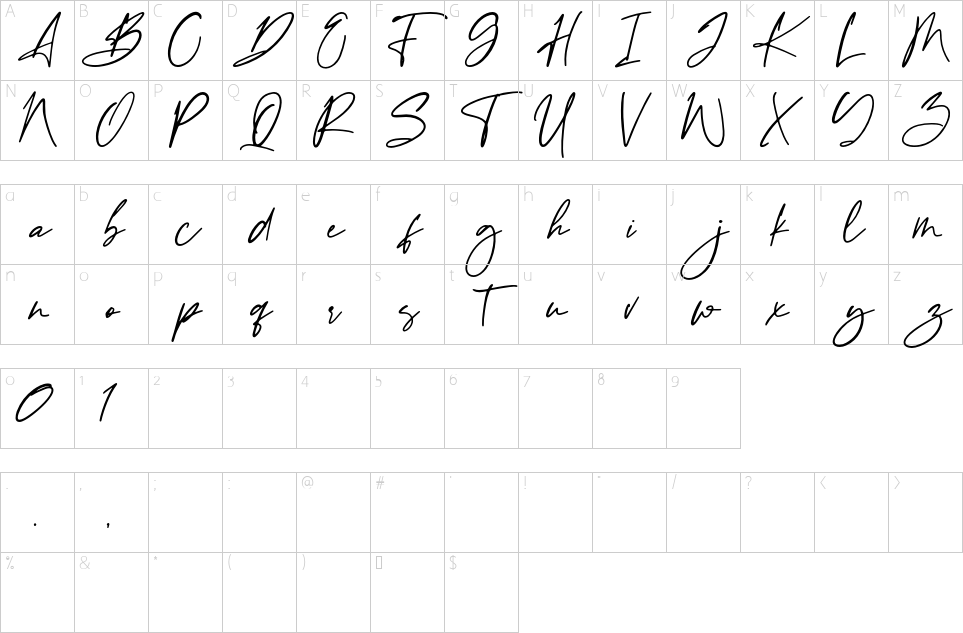
Baekrajan é uma fonte moderna e elegante que oferece um equilíbrio perfeito entre simplicidade e profissionalismo. Desenvolvida pelo designer não informado, a Baekrajan está disponível para download tanto em versão Windows quanto Mac. Com seus traços finos e formas levemente curvilíneas, esta fonte adquire um toque sofisticado às suas criações digitais. É ideal para aplicativos de design gráfico ou publicidade online que buscam uma fonte moderna sem perder seu caráter único. Baekrajan já foi baixada 63,549 vezes e continua a ser popular por sua versatilidade e beleza estética. Não perca essa fonte gratuita para experimentar o estilo único de Baekrajan em suas próximas criações digitais.